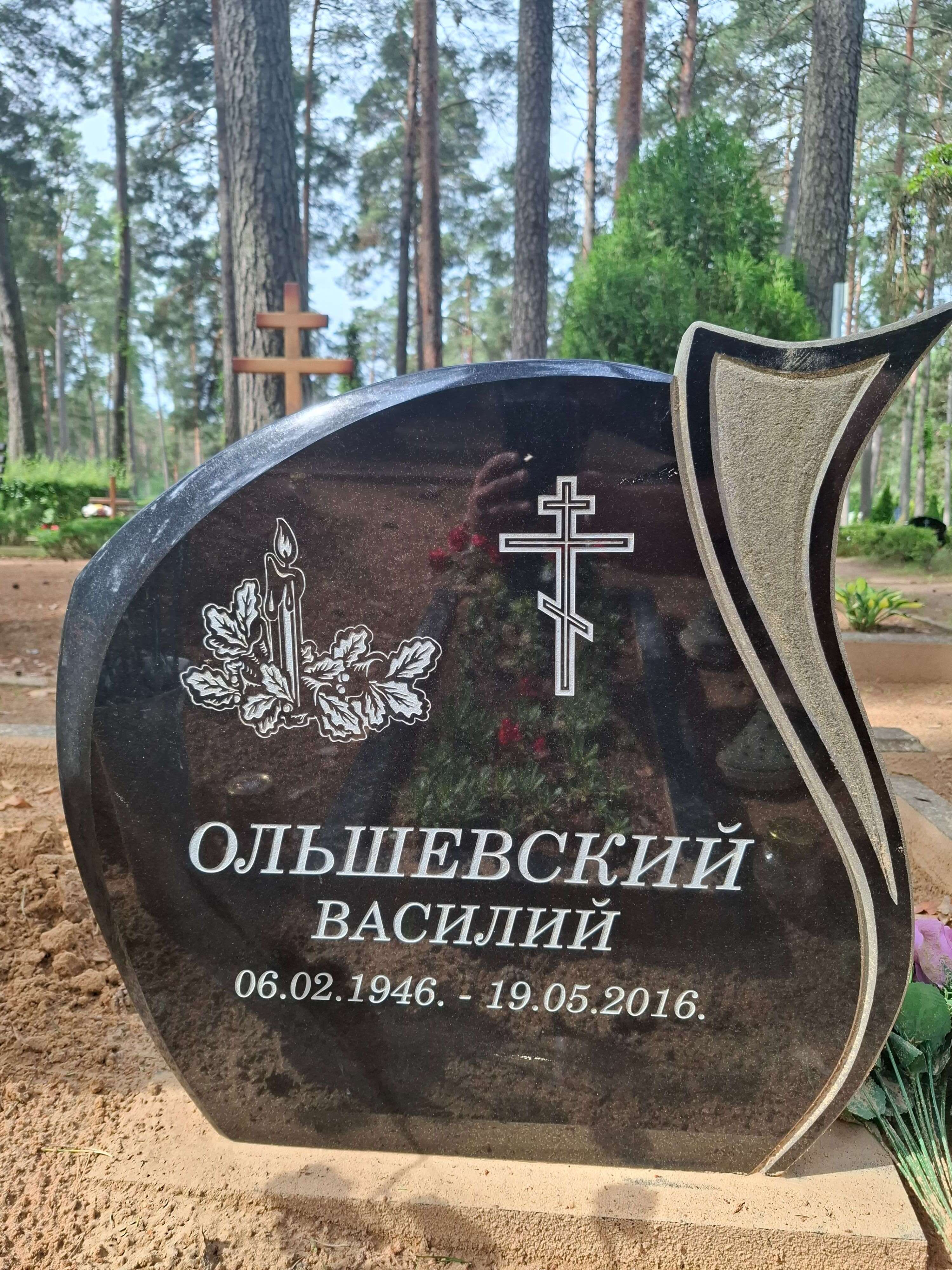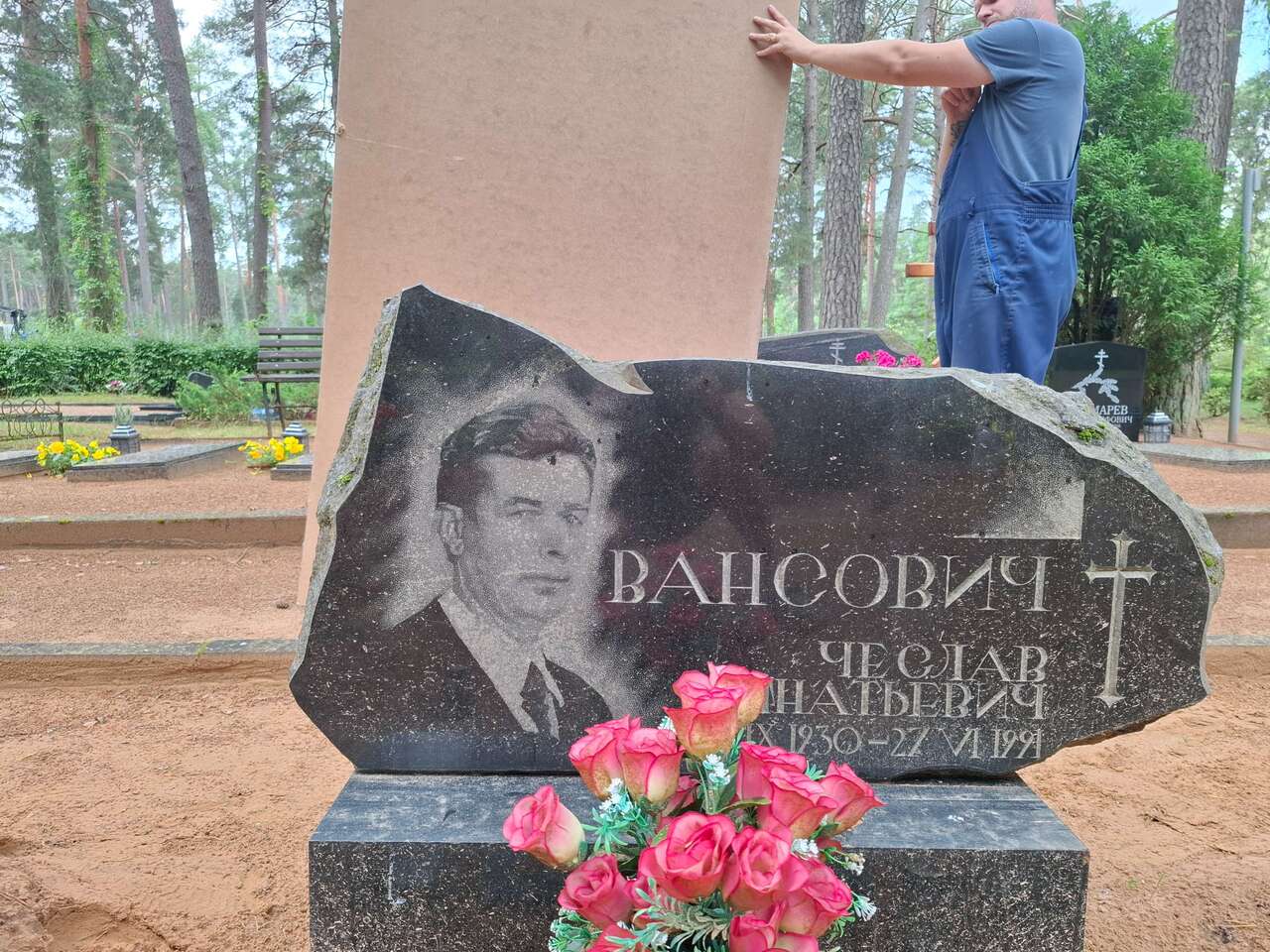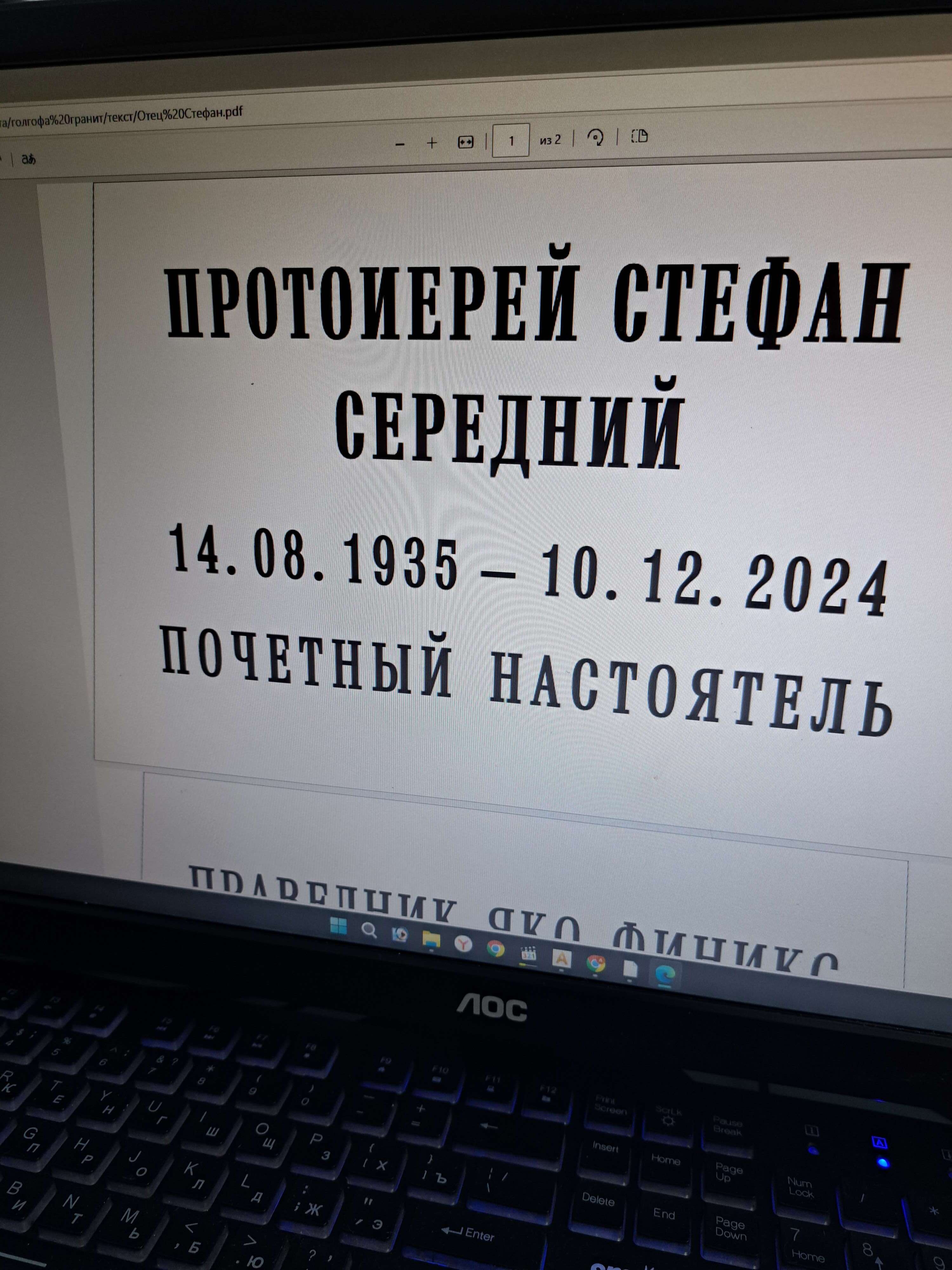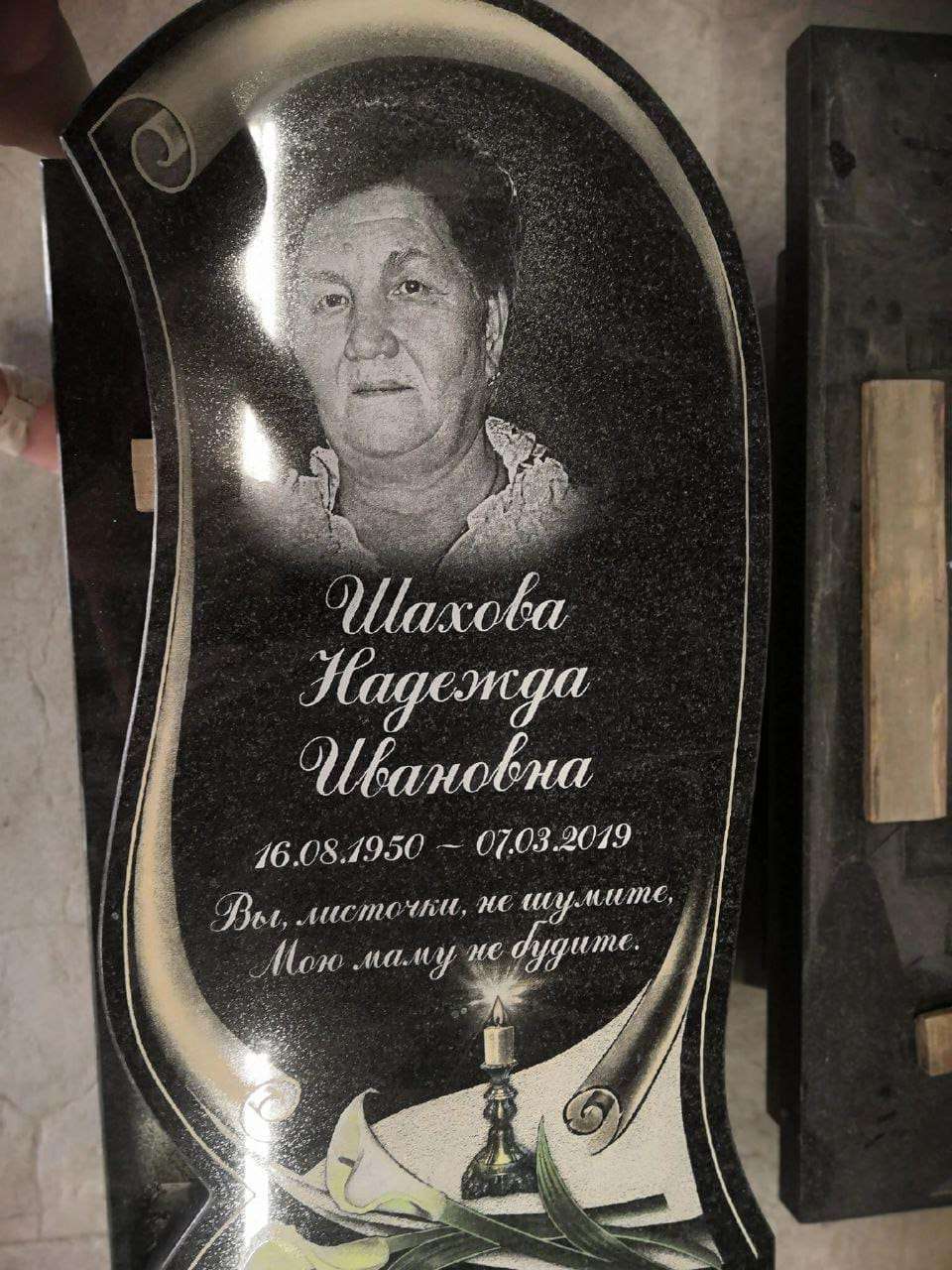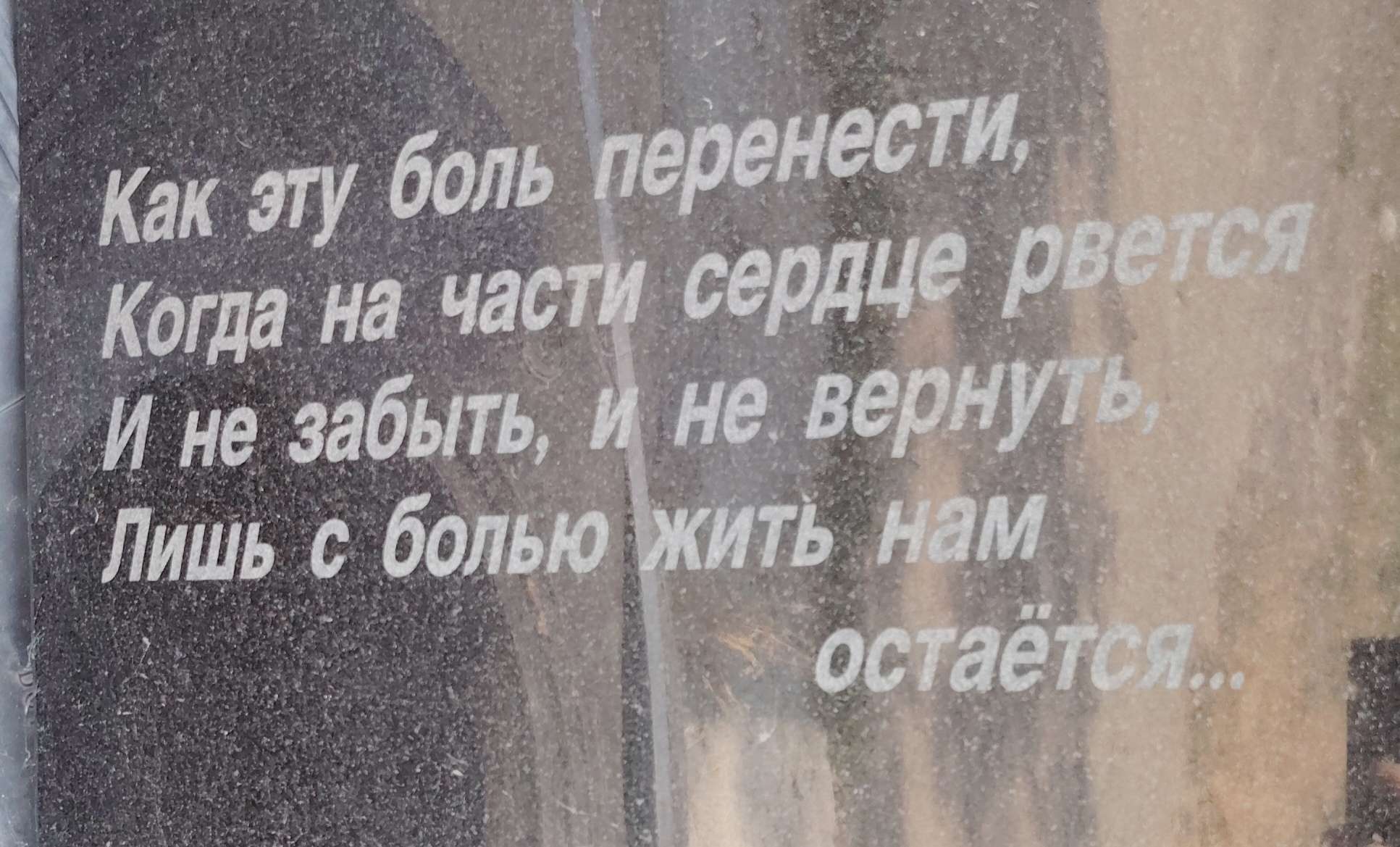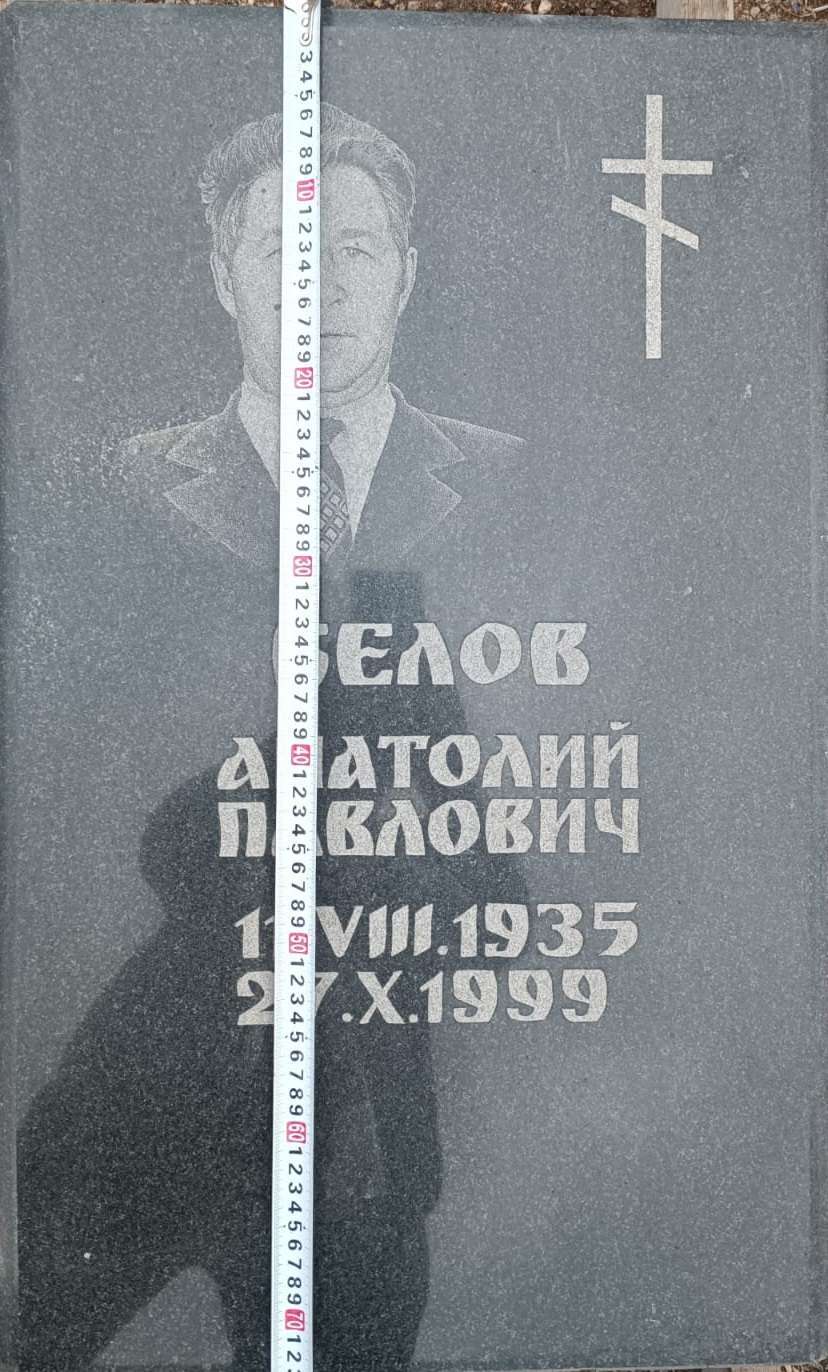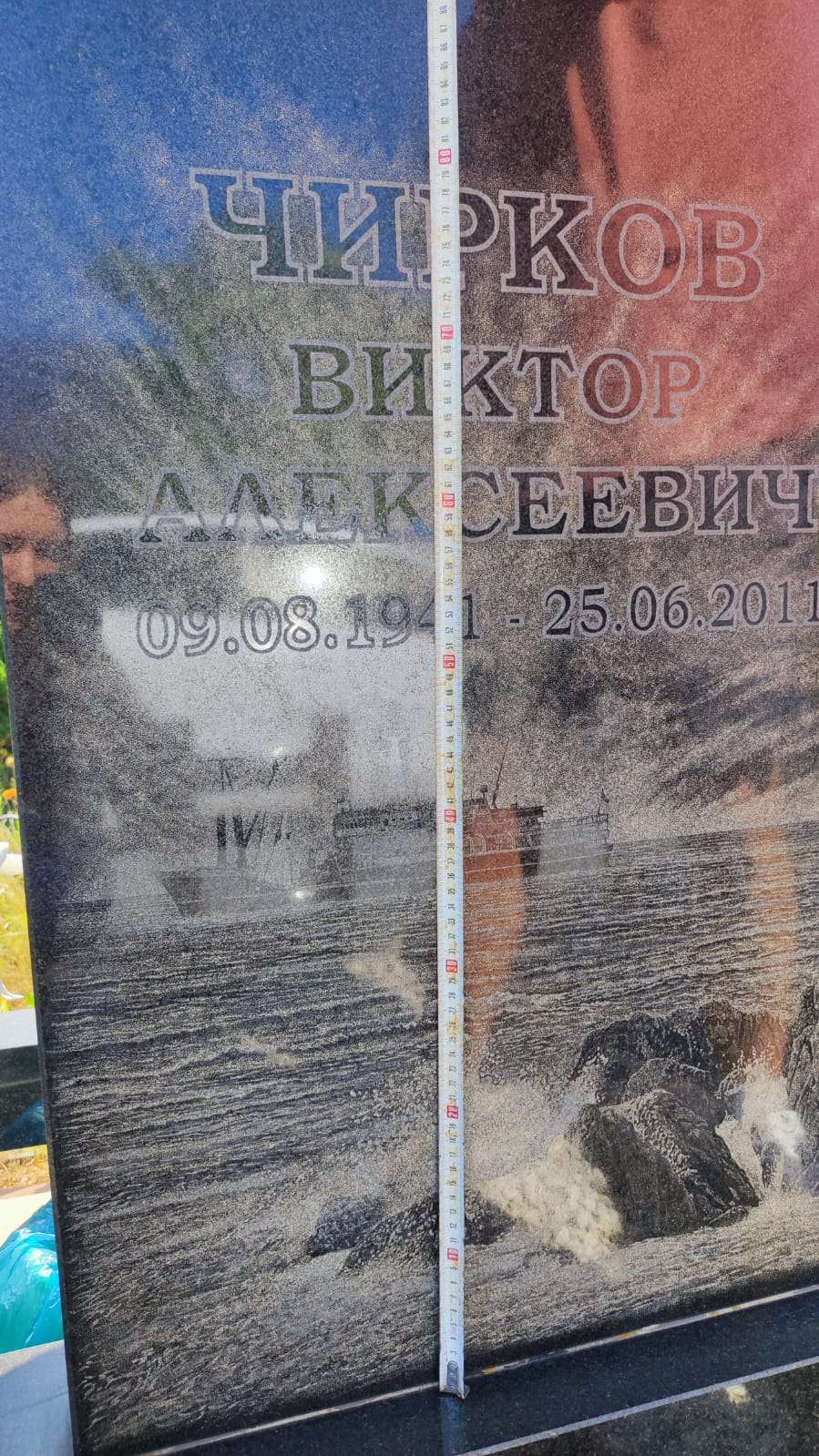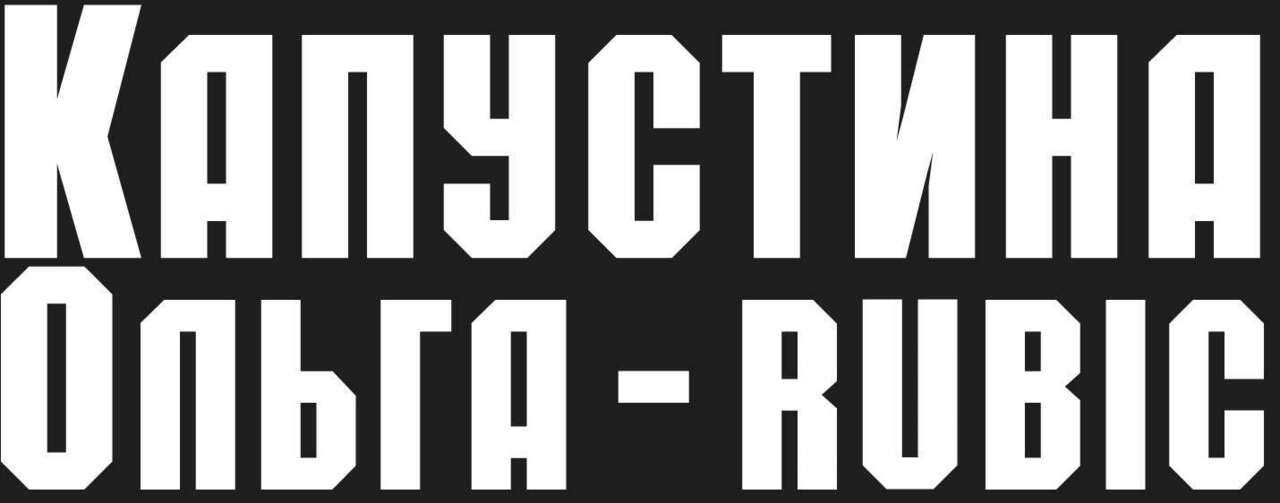
Марсианин Опубликовано 8 июля, 2025 Всем привет,что за шрифт кто знает подскажите
Storn Опубликовано 12 июля, 2025 4 минуты назад, lad14 сказал: Здравствуйте, помогите найти шрифт шрифт ArtScript
Melnichsd Опубликовано 17 июля, 2025 Добрый день, подскажите название шрифта
kamnerez Опубликовано 17 июля, 2025 @Melnichsd https://ofont.ru/view/4123 или вообще самый банальный Arial 1
kamnerez Опубликовано 18 июля, 2025 @aazt руками делали, все буквы разные. Попробуй Мирослав https://www.ph4.ru/fonts_fonts.php?fn=slav&cat=rus&id=1 1
drshutka Опубликовано 25 июля, 2025 Доброго дня всем! Кто подскажет, что за шрифт?
Владимир65765187 Опубликовано 28 июля, 2025 Помогите найти шрифт, похож на Times New Roman, но не он. Или ручник?
JuliaN Опубликовано 28 июля, 2025 Похоже на Bookman фамилия Bookman old style 1
NatAlex Опубликовано 8 августа, 2025 Добрый день! Спасите! Может кто знает что за шрифт
Romeo Опубликовано 1 сентября, 2025 Друзья,помогите пжста найти шрифт. Вроде знакомый, но что то найти не получается в моей базе. Спасибо
АлександрTv Опубликовано 1 сентября, 2025 Здравствуйте, помогите, пожалуйста, с шрифтом.
Юрок Опубликовано 2 сентября, 2025 (изменено) Ребята, есть у кого-нибудь такой шрифт в формате .ttf ? Изменено 2 сентября, 2025 пользователем Юрок
Storn Опубликовано 2 сентября, 2025 товарищи! помогите определить шрифт
Soaring man Опубликовано 2 сентября, 2025 @Storn так это ж anastasiascript 1